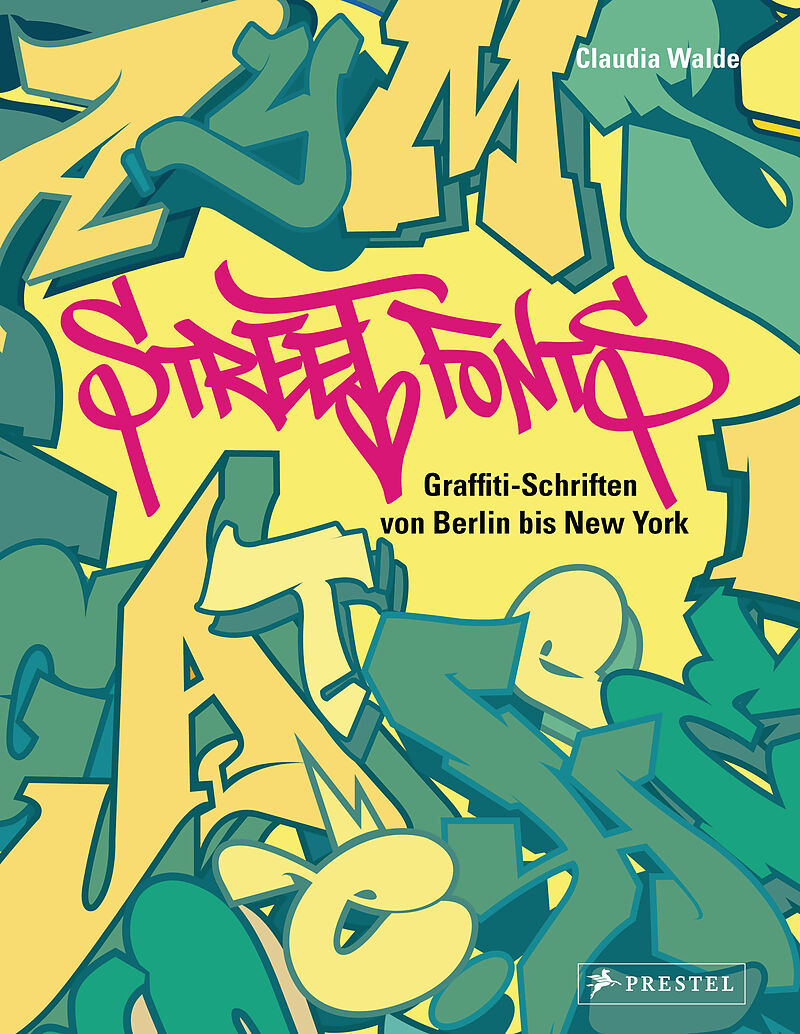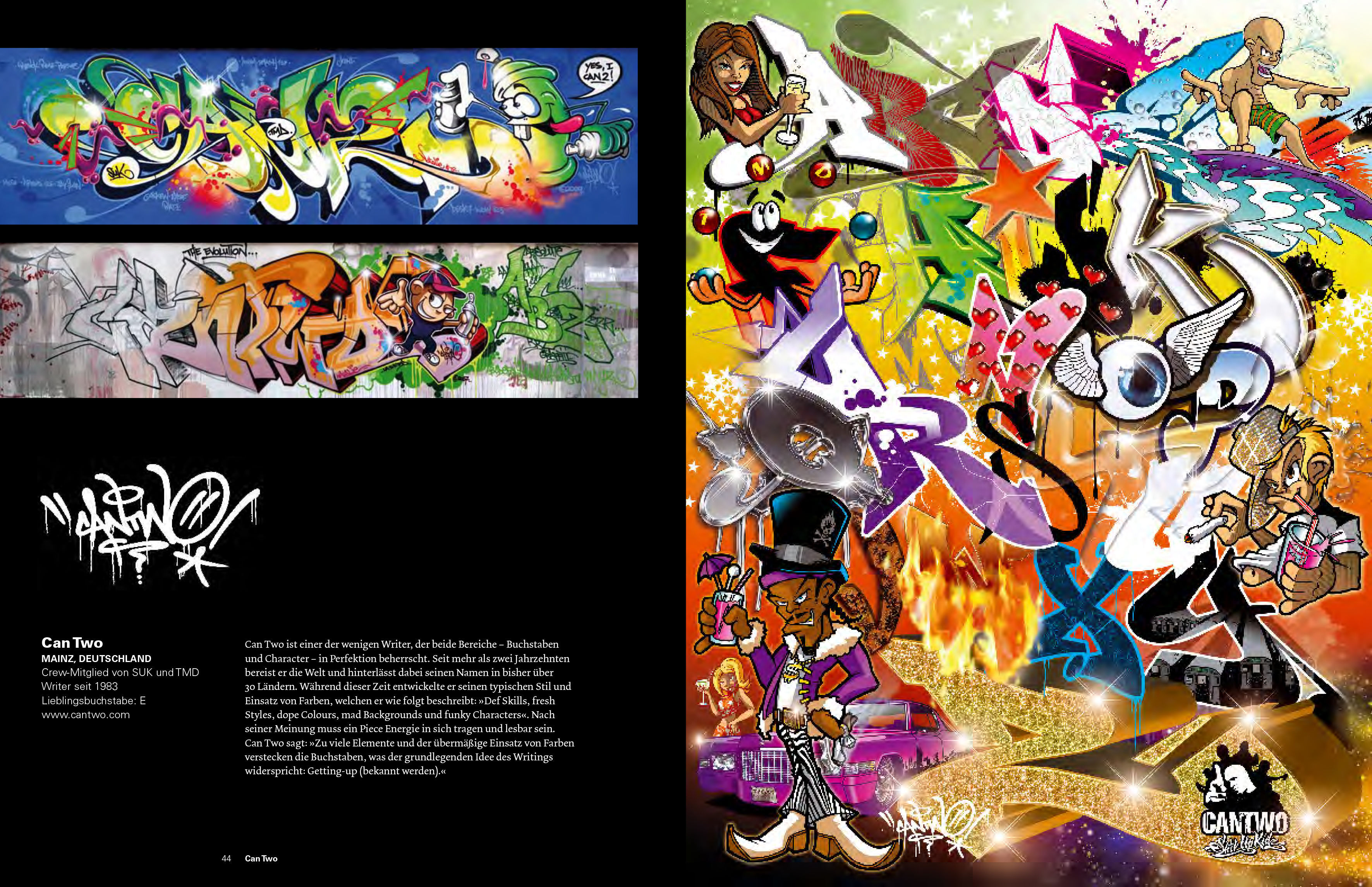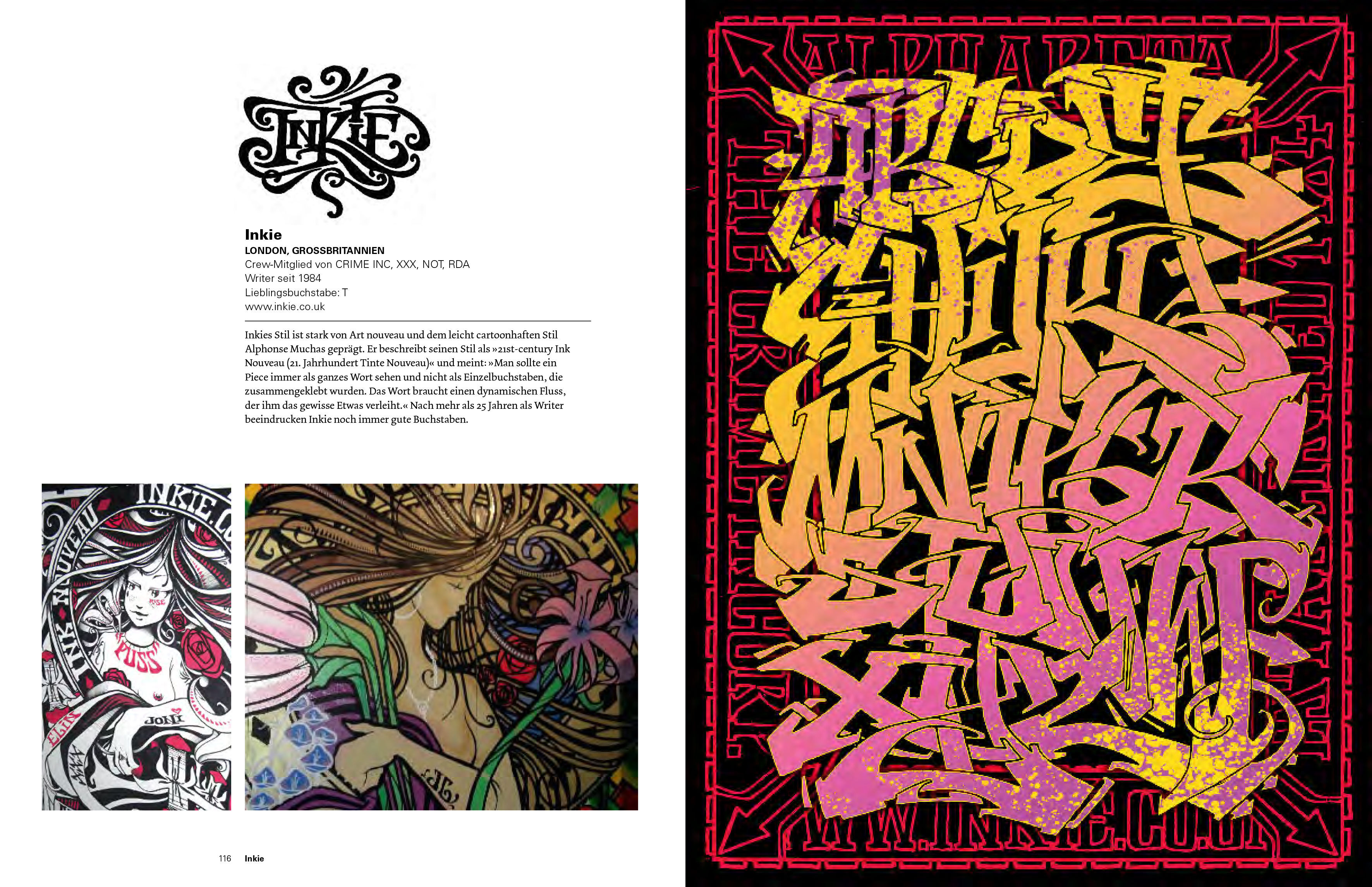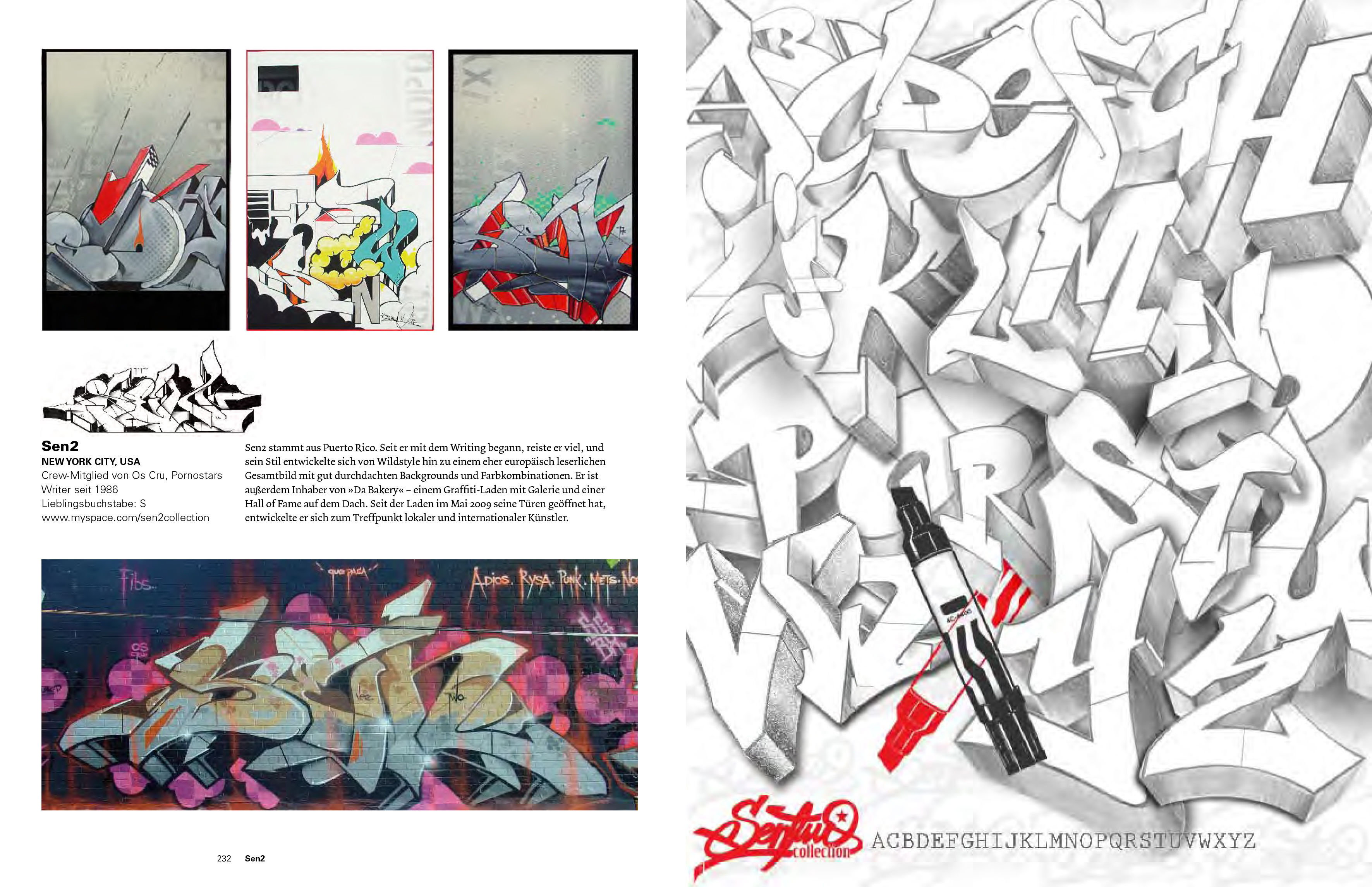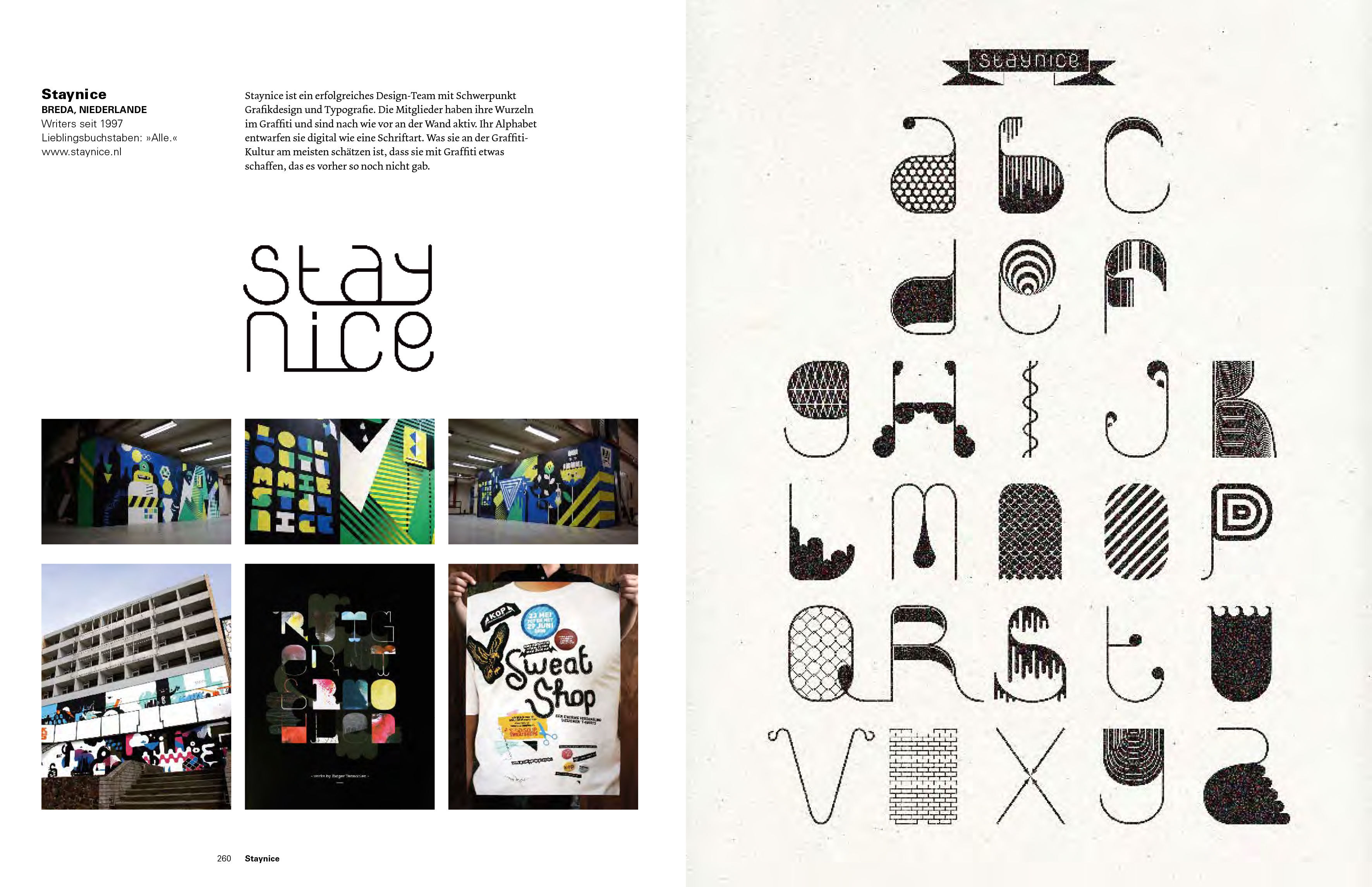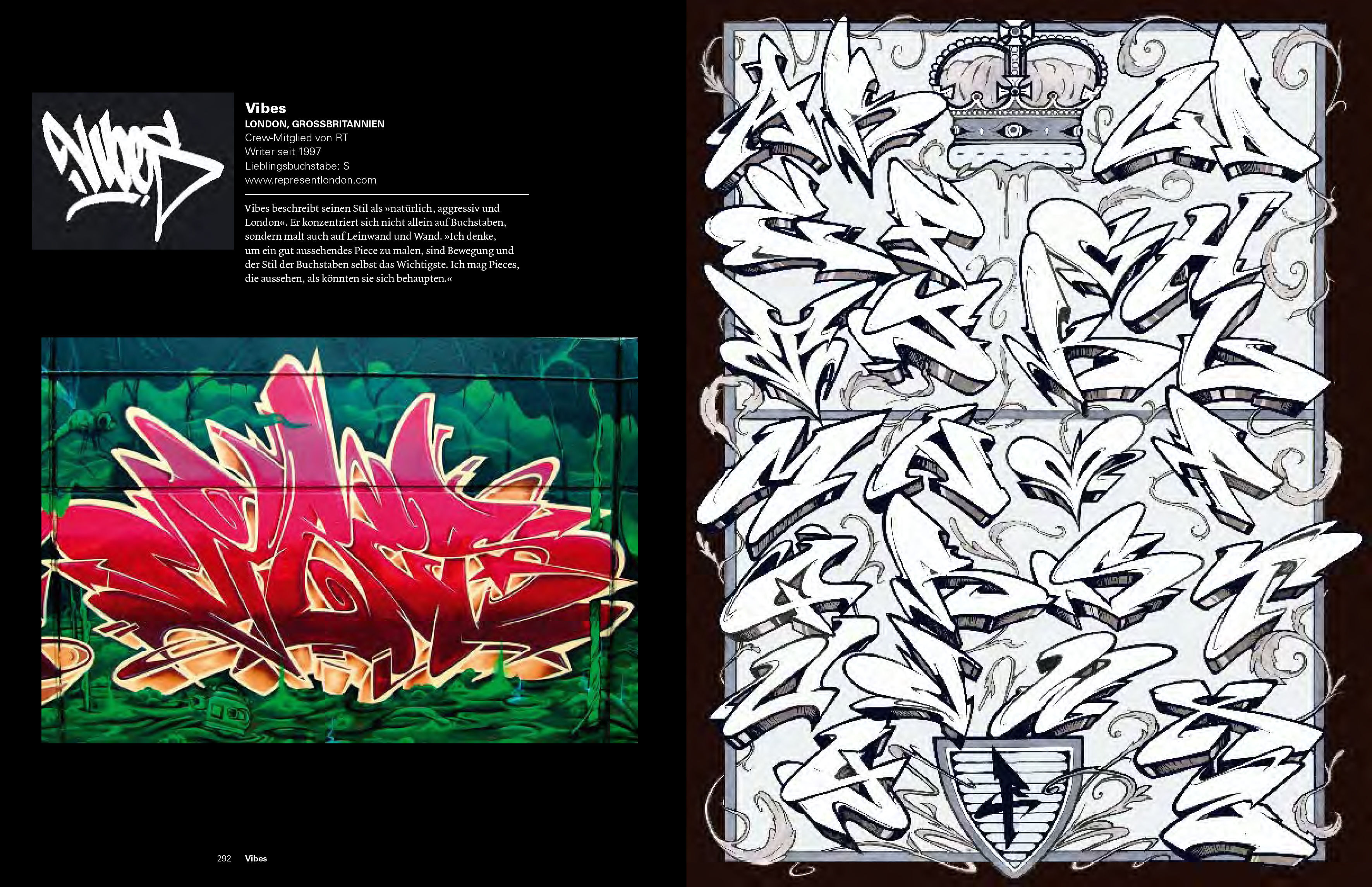
Street Fonts
Das Alphabet der Straße Dieser Band ist die perfekte Inspirationsquelle für Designer, Grafiker, Gestalter, Typografen und alle, die sich für Street Art interessieren. Mit mehr als 150 eigens für diesen Band entworfene Schriften von internationalen Graffiti-Art...